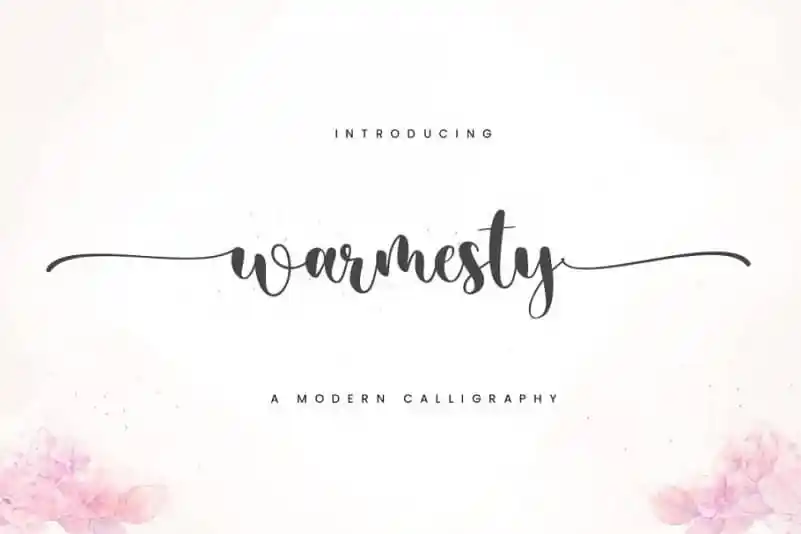
Warmesty Calligraphy Font – Download Grátis
A Warmesty Calligraphy Font é uma excelente escolha para aqueles que procuram um efeito elegante e romântico em seus designs. Criada pela Sronstudio, esta fonte de script oferece uma variedade única de swashes tanto nos começos quanto nas finais das letras, resultando em um estilo encantador ideal para fazer belas inscrições amorosas ou qualquer outro projeto que exija graciosidade e delicadeza. Com seu conjunto completo de letras minúsculas com swashs e números, a Warmesty é uma fonte perfeita para criação artística, identidades corporativas, convites, decoração de papelaria, designs de casamentos, posts na mídia social, anúncios, embalagens de produtos, design dos produtos, etiquetas, fotografia e até mesmo como marca d’água em eventos especiais ou qualquer outro propósito. Seja para um evento especial ou simplesmente personalizar uma peça de arte, a Warmesty é perfeitamente adaptável a diferentes ambientes criativos.